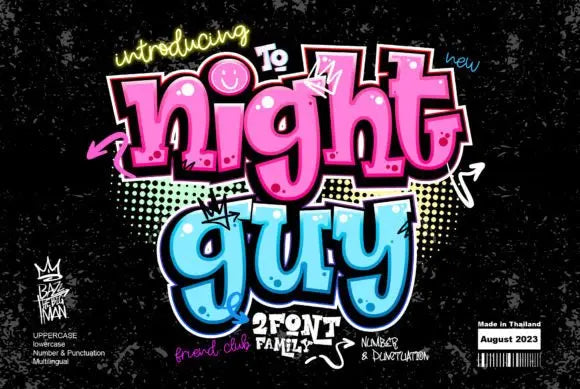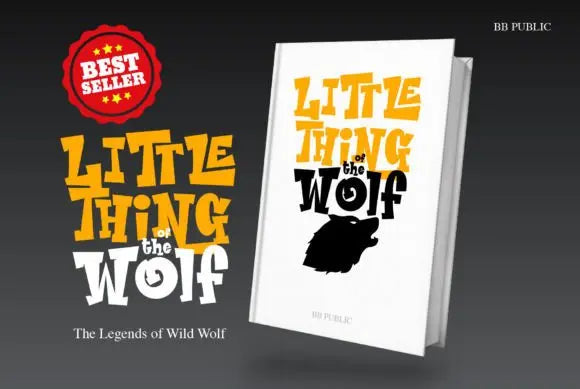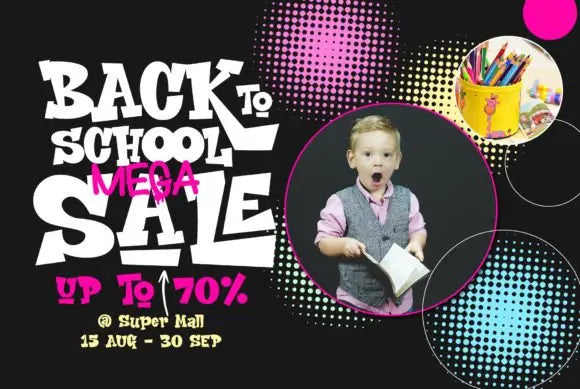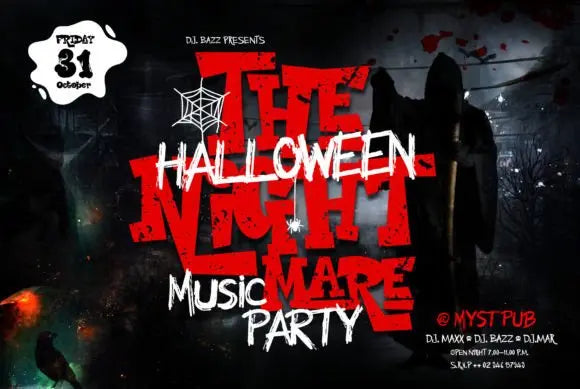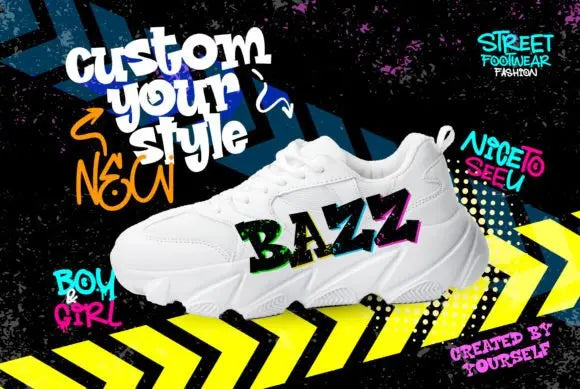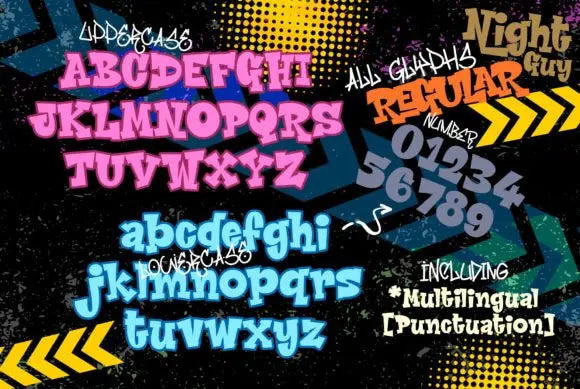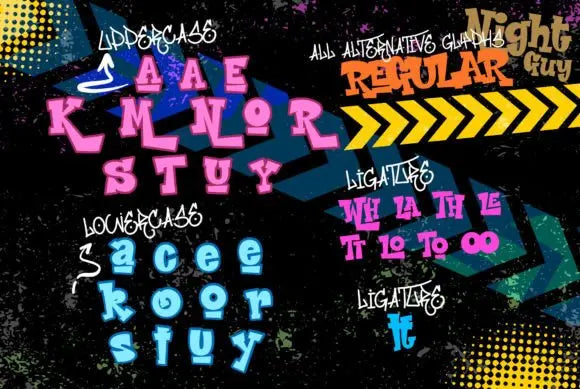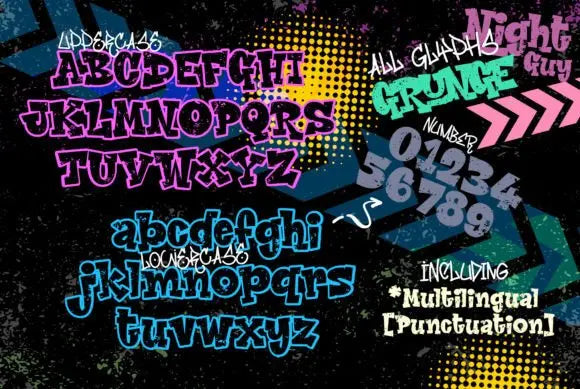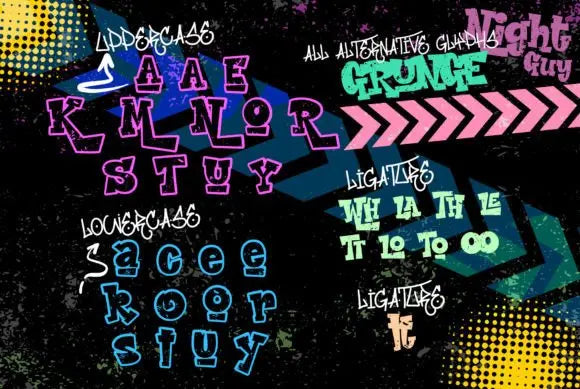
Fuente Night Guy
Night Guy es una fuente de graffiti increíblemente única y atrevida. ¡Diseñada magistralmente para convertirse en una verdadera favorita, esta fuente tiene el potencial de llevar cada una de tus ideas creativas al más alto nivel! Crea diseños de inspiración urbana con facilidad.
Llena de confianza y personalidad, Night Guy Font ofrece opciones ilimitadas para expresar tu estilo.